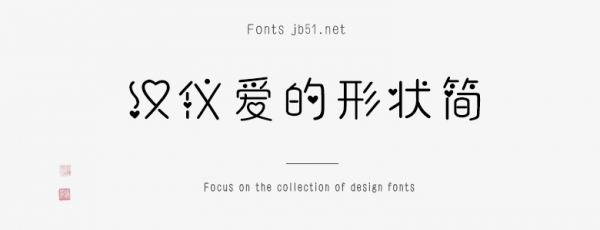
漢儀愛(ài)的形狀簡(jiǎn)是由漢儀字庫(kù)出品,字體筆觸適中,字形端正,以心形圖案作為點(diǎn)綴,具有很好的視覺(jué)感,適合應(yīng)用于藝術(shù)設(shè)計(jì)、平面宣傳設(shè)計(jì)、網(wǎng)頁(yè)設(shè)計(jì),書(shū)法字帖等領(lǐng)域,需要的朋友可以前來(lái)本站下載。